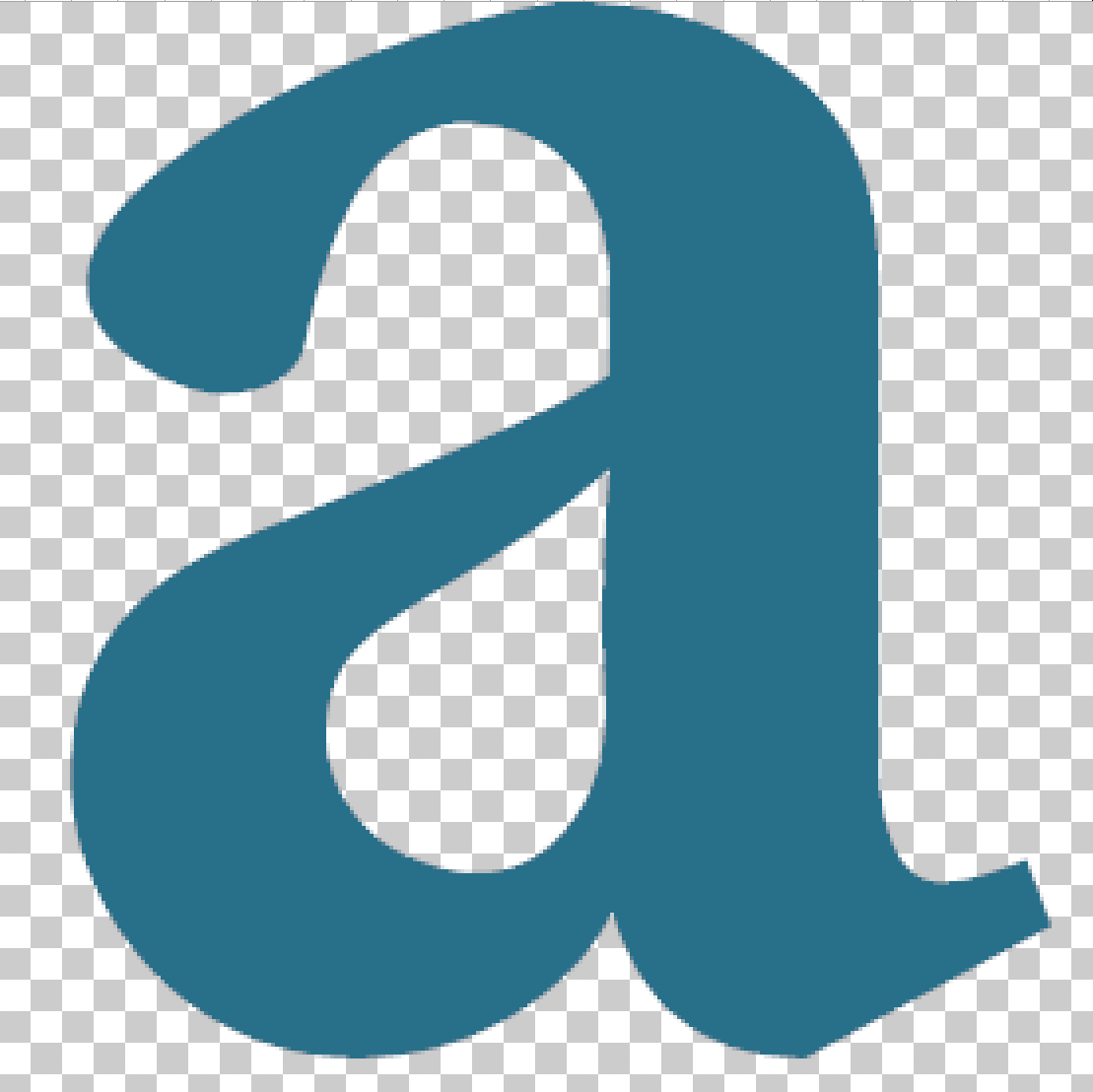
Nein, leider habe ich nur diesen Buchstaben «a». Stammt aus dem Logo von «Adrians Weingut». Habe bereits in meiner Schriftensammlung gesucht, aber den genauen Typ finde ich nicht. (Nähe «Adobe Gaslon»?)
Ja, Minion kommt schon sehr nahe. Ich frage mich, ob die Schrift geändert wurde oder ob es sie im Original gibt.